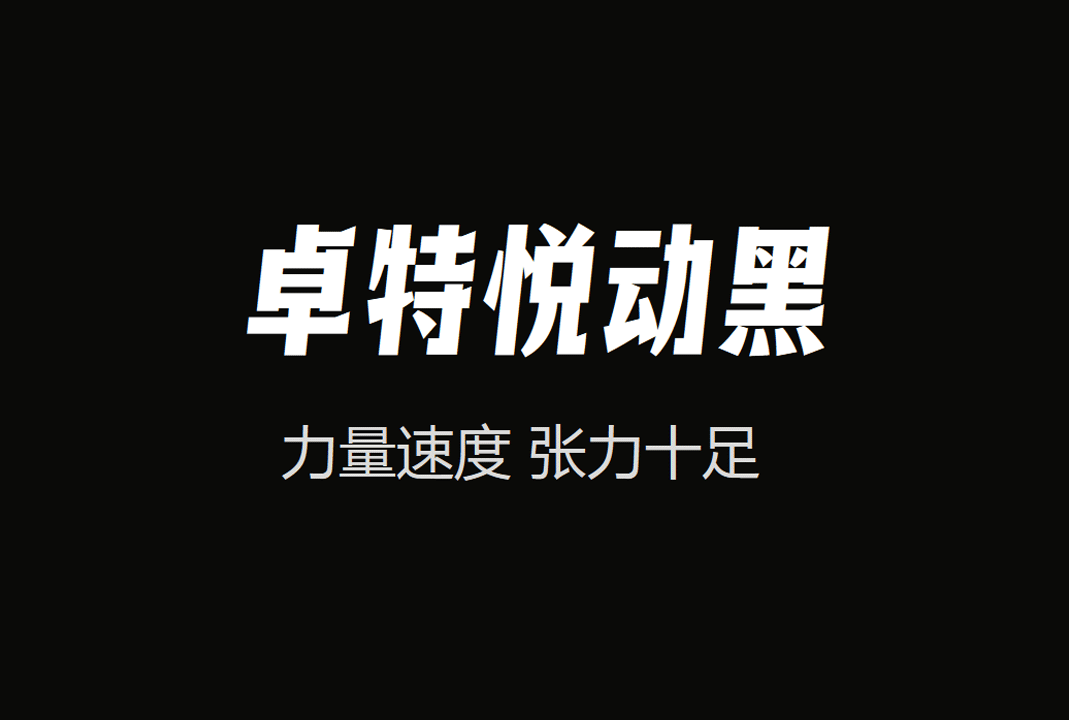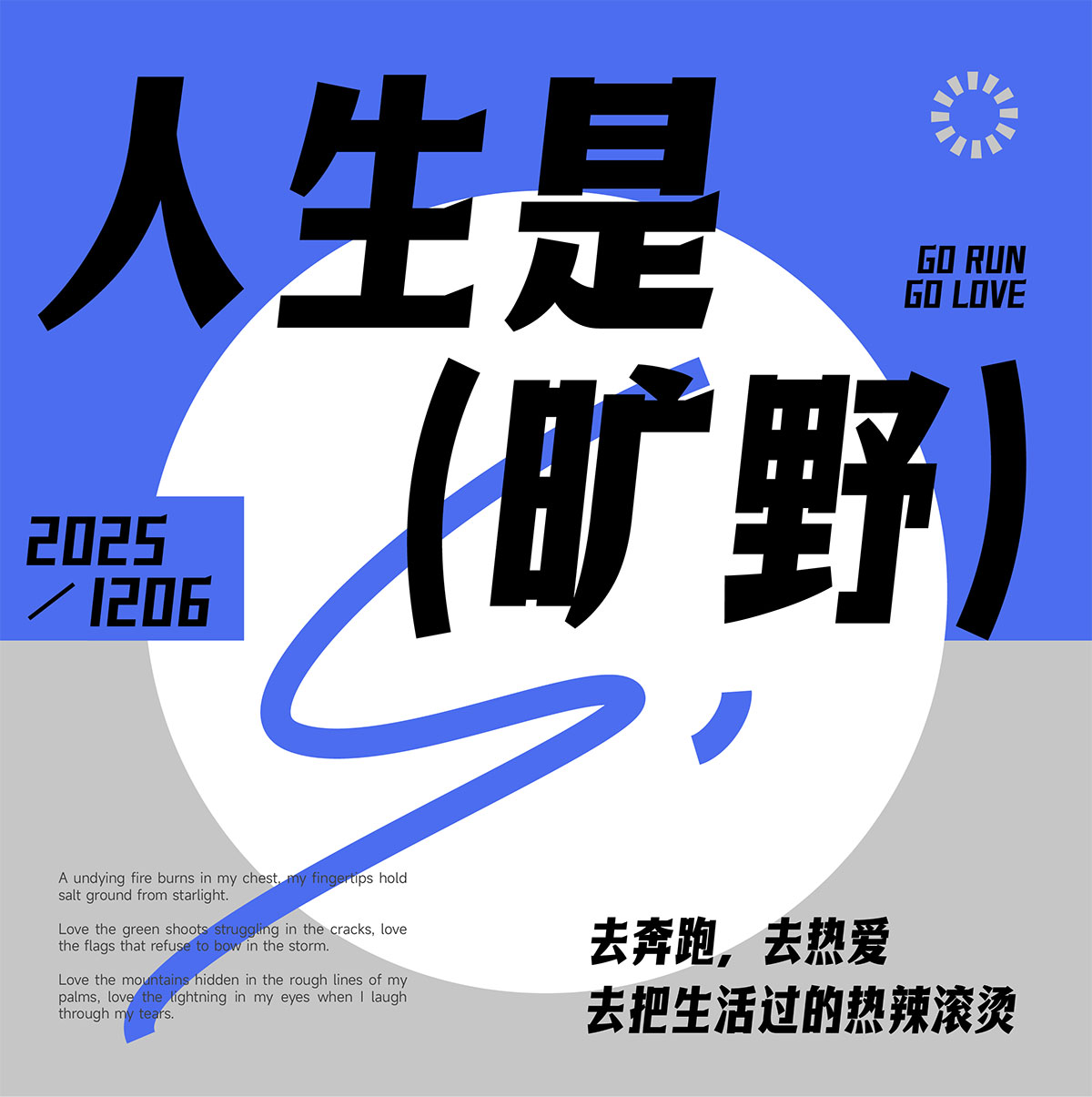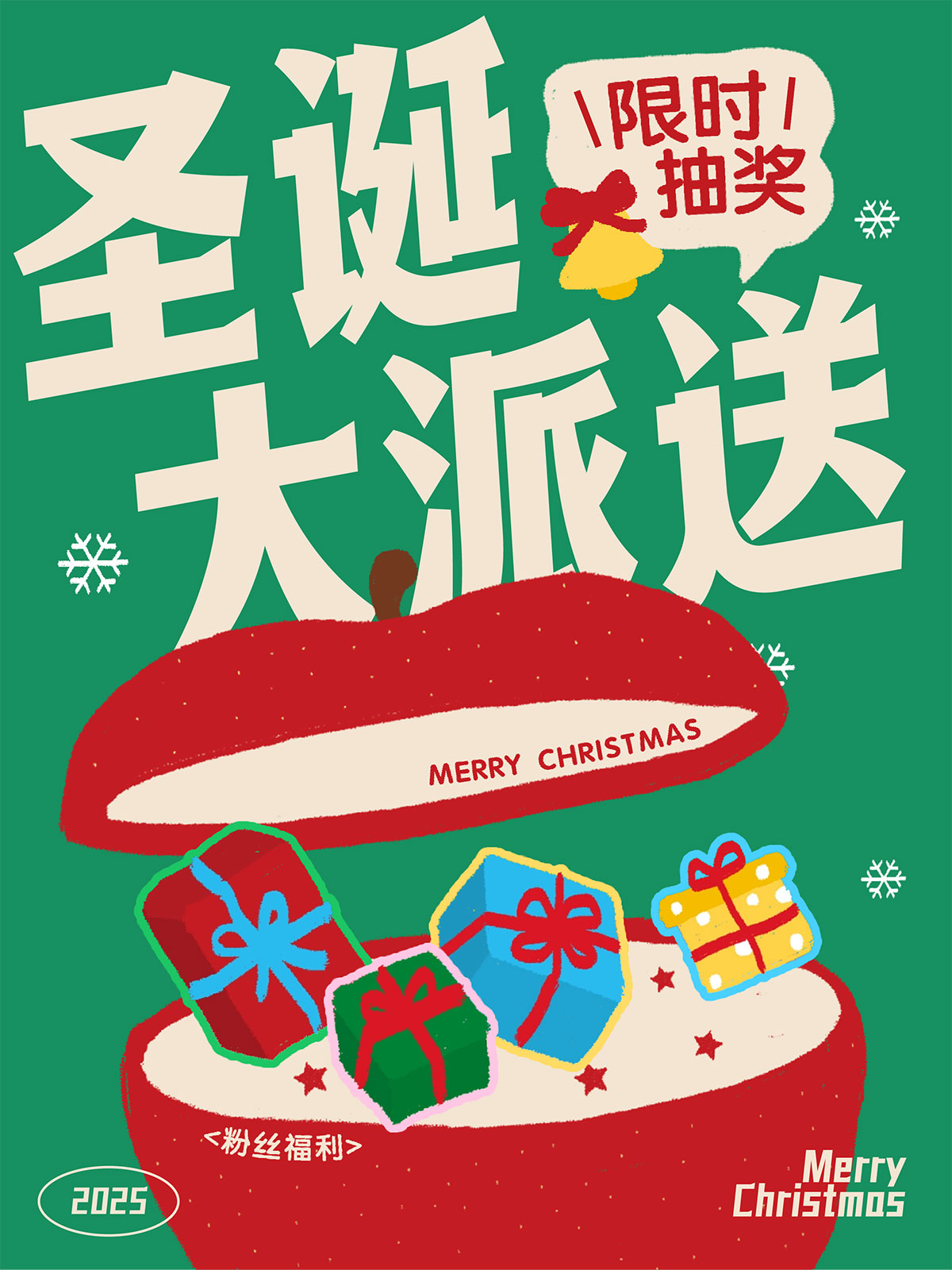
卓特悦动黑是由卓特视觉携手国内知名字体设计师刘兵克,为创意人群打造三款风格迥异的免费字体之二。
卓特悦动黑字形高挑饱满,笔画厚实有力,富有强烈的力度感和动势。结合近代印刷美术字特征,横画外侧带有独特的尖角装饰,适合各类专业场景使用。包含 GB2312-80 标准中的 6763 个简体汉字及 420 个常用字符,共收录 7183 个字符,可满足日常办公、设计创作、品牌宣传等多元场景的字体使用需求。
字体应用展示: